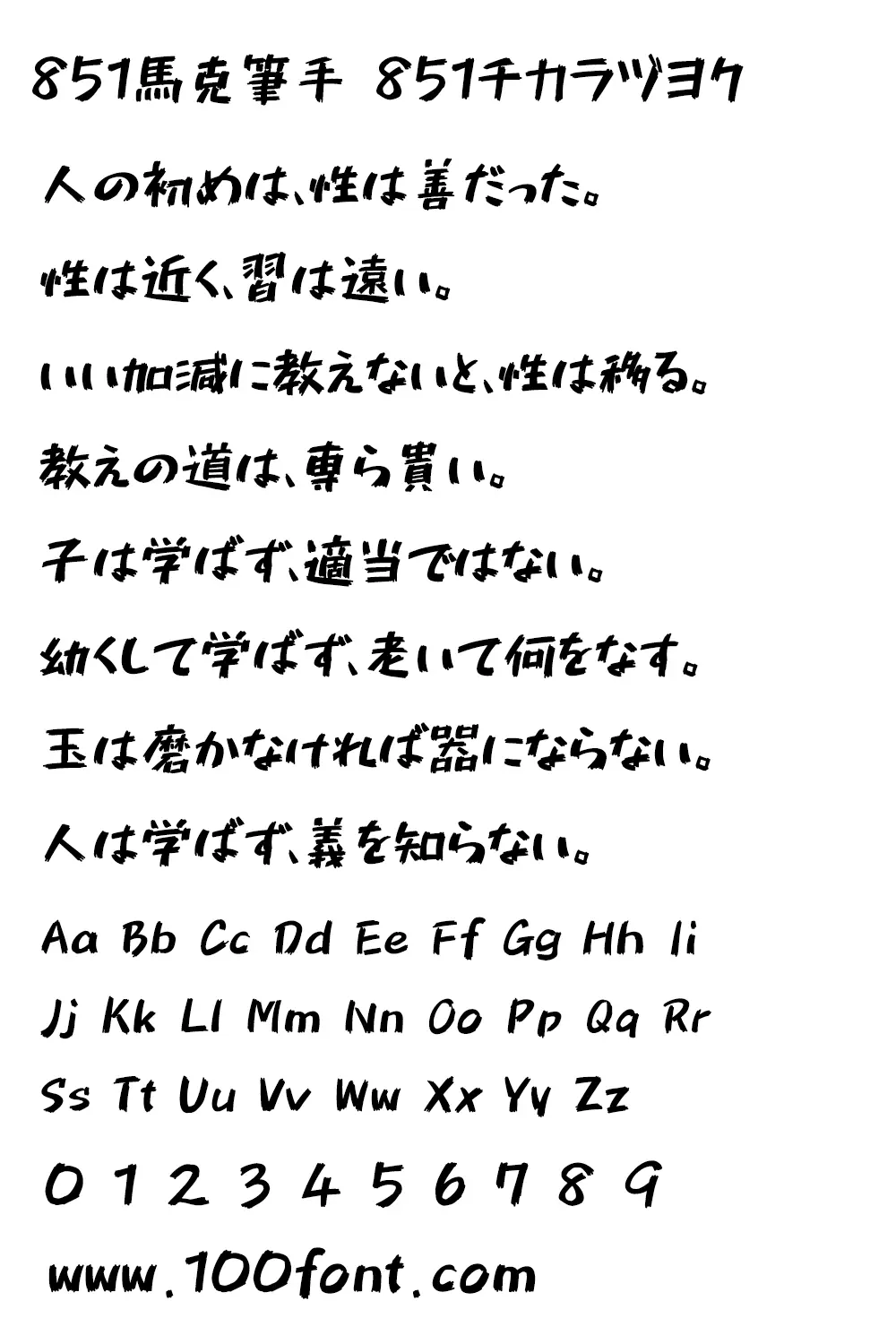
851馬克筆手寫體(51チカラヅヨク)是日本設計師 8:51:22 pm 設計的一款馬克筆手寫體,橫細豎粗,行筆飄逸,當前字符數:3859個字符(不包括空格)。
對應文字:平假名、片假名、拉丁文字(英語)、數字、符號(少許)、漢字(常用漢字+少許)
注意:這款字體適用於繁體和日文,不適用於簡體中文,容易缺字。